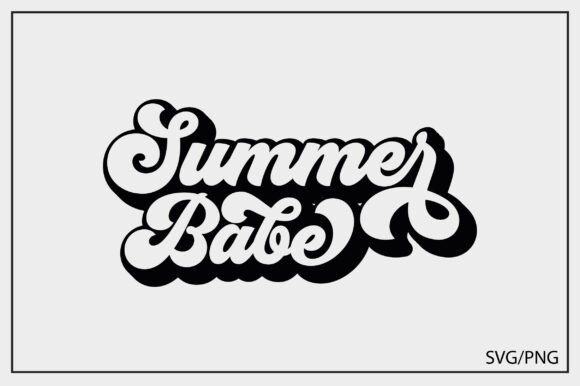
Summer Babe Retro Font Typography
Sombrinhas de Verão: A Fonte Retro para Seus Projetos
** Se você está procurando por uma fonte que evoca a sensação de calor e liberdade do verão, então você está no lugar certo! A **Summer Babe Retro Font Typography** é uma fonte incrível que transportará seus projetos para um mundo de cores vibrantes e estilos clássicos. **Características da Fonte
** * **Formato:** SVG e PNG de alta qualidade * **Design:** Fonte retro inspirada na década de 80 e 90 * **Tipografia:** Perfeita para projetos que precisam de um toque de nostalgia e charme * **Flexibilidade:** Pode ser usada em vários projetos, desde sites e aplicativos até materiais de marketing e publicidade **Vantagens da Fonte
** A **Summer Babe Retro Font Typography** é uma fonte incrível que pode agregar um toque de charme e estilo a qualquer projeto. Com suas características únicas e flexibilidade, é uma escolha perfeita para designers, desenvolvedores e empresas que precisam de uma fonte que represente sua marca de forma única e criativa.